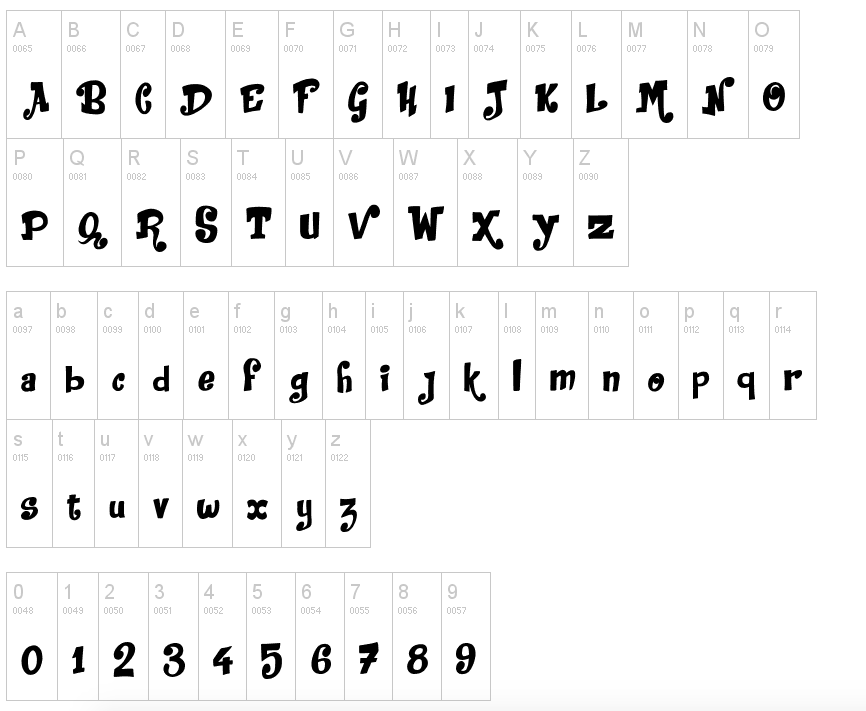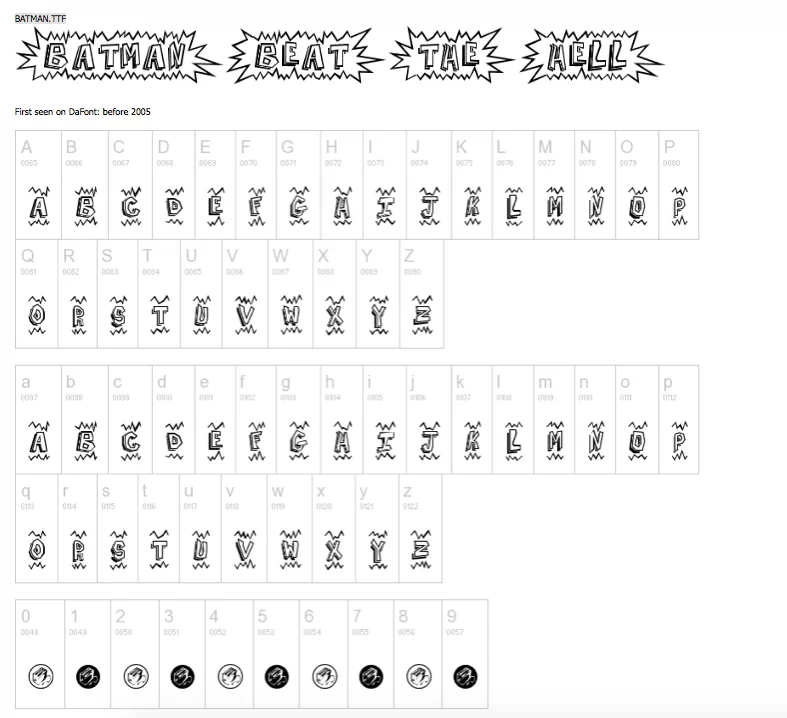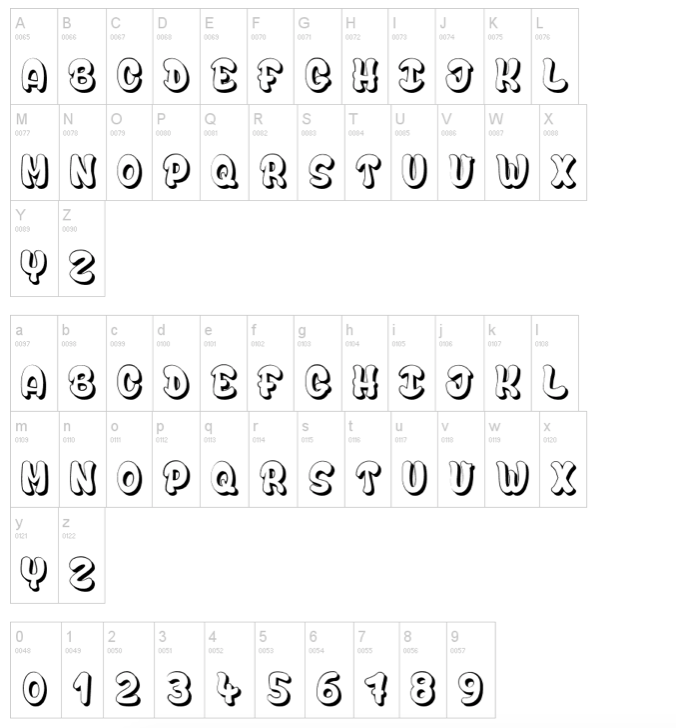
Die 20 besten Zeichentrick- und Comic-Schriftarten
Veröffentlicht: 2022-06-30Comics und Zeichentrickbücher dienen der Unterhaltung. Sie sollten in keiner Weise langweilig oder repetitiv sein. Nicht nur guter Inhalt, sondern auch erstaunliche Grafiken sind hilfreich, um Ihr Comicbuch zu einem Bestseller zu machen.
Abgesehen von Bildern spielt der Schriftstil Ihres Buches eine große Rolle bei der Gewinnung von Lesern. Die Verwendung des gleichen Schriftstils über Jahre hinweg ist für Ihre Leser ab einem bestimmten Punkt möglicherweise nicht mehr ansprechend.
Daher ist es ratsam, Ihren Schreibstil ständig mit ansprechenden Schriftarten zu aktualisieren, um sich besser zu engagieren.
Wir haben die konformistische Welt der Comic Sans Ms verlassen, um innovative Cartoon- und Comic-Schriftarten auszuwählen, die den Inhalt stilvoller, funkiger und unterhaltsamer aussehen lassen.
Werfen Sie einen Blick auf coole, ausgefallene Zeichentrick- und Comic-Schriftarten , die Ihren Inhalten zusätzlichen Schwung verleihen können.
FETT GEDRUCKT
Wenn Sie ein paar Wörter hervorheben oder die Aufmerksamkeit der Leser sofort auf sich ziehen möchten, ist Fettschrift perfekt. Schauen Sie sich die trendigen fetten Schriftarten an, die sofort ins Auge fallen.
Badaboom
Badaboom ist eine perfekte Schriftart für Ausrufe und Titel. Inspiriert von der Kunst jahrelanger Comics, ist es sicherlich eine beeindruckende Schriftart zum Ausprobieren.
Das Erstaunliche ist, dass Sie keinen einzigen Cent ausgeben müssen, um es zu benutzen. Es kommt sowohl im OPENTYPE- als auch im TRUETYPE-Format. Im Laufstil gestaltet, ist es informell und passt daher gut zu lustigen Comics.
Super Mario 2
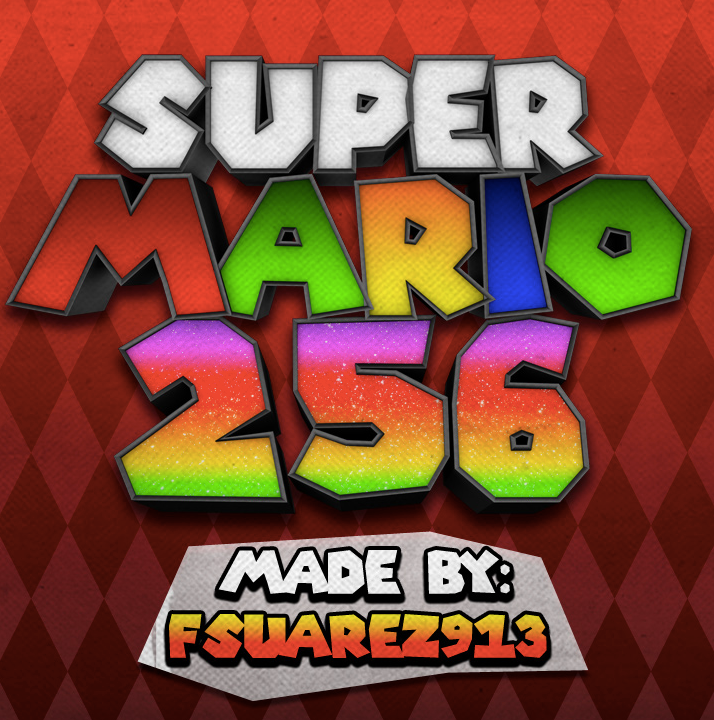
Es könnte nichts Besseres geben als Super Mario 2, um dramatische Titel oder Schlagzeilen zu machen. Es ist robust und dennoch stilvoll und peppt Ihre Inhalte perfekt auf.
Diese Schriftart ist vom Mario-Schriftzugstil inspiriert, der erstmals auf dem Titelbildschirm von Super Mario Bros.3 zu sehen war. Kühn und einflussreich, SuperMario 2 ist ein besonderer Leckerbissen für Ihr Comic- und Zeichentrickbuch.
Zurück Probleme
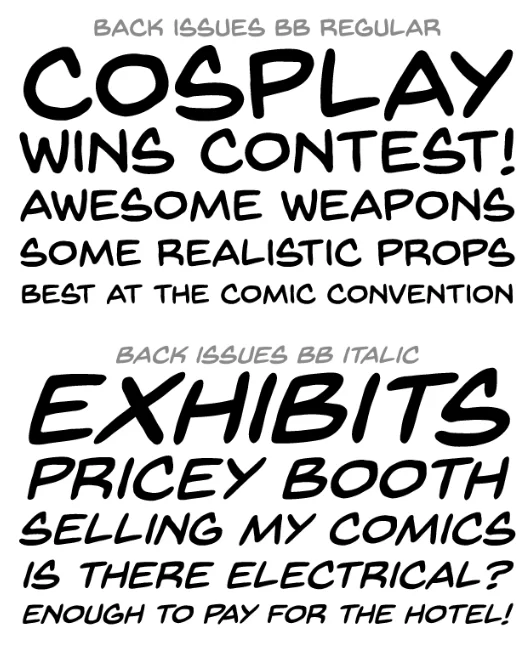
Back Issues kommt im Laufstil und sieht am besten mit humorvollen Inhalten aus. Es ist in normaler, fetter und kursiver Schrift verfügbar, um mit Ihren Inhalten so zu spielen, wie Sie möchten.
Für ästhetisch ansprechende Geschichten und Dialoge können Sie frühere Ausgaben in MAC TTF, OPENTYPE und PC TFF herunterladen. Es hat eine beruhigende Wirkung auf die Augen und fügt dem Inhalt ein interessantes Element hinzu.
SPASS
Karikatur
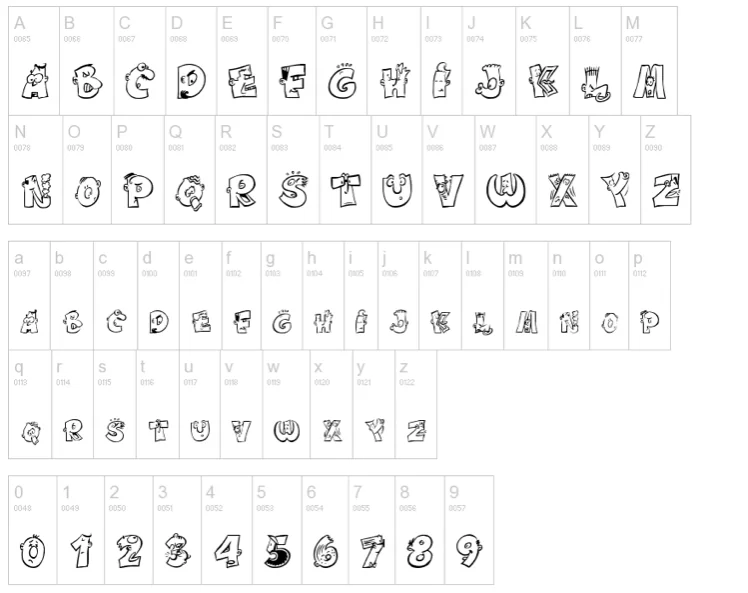
Karikatur ist ein ansprechender Schriftstil, der selbst ein gewöhnliches Gespräch lesenswert machen kann. Jeder einzelne Buchstabe dieses Schriftstils ist durchdacht gestaltet, um die Dinge fast sofort interessant zu machen.
Nicht nur alphabetische Buchstaben, sondern auch Zahlen und verschiedene Zeichen in Caricature, von denen jedes einem lustigen Gesichtsausdruck ähnelt, um Ihrem Buch einen Mehrwert zu verleihen.
Skizzenhafter Comic
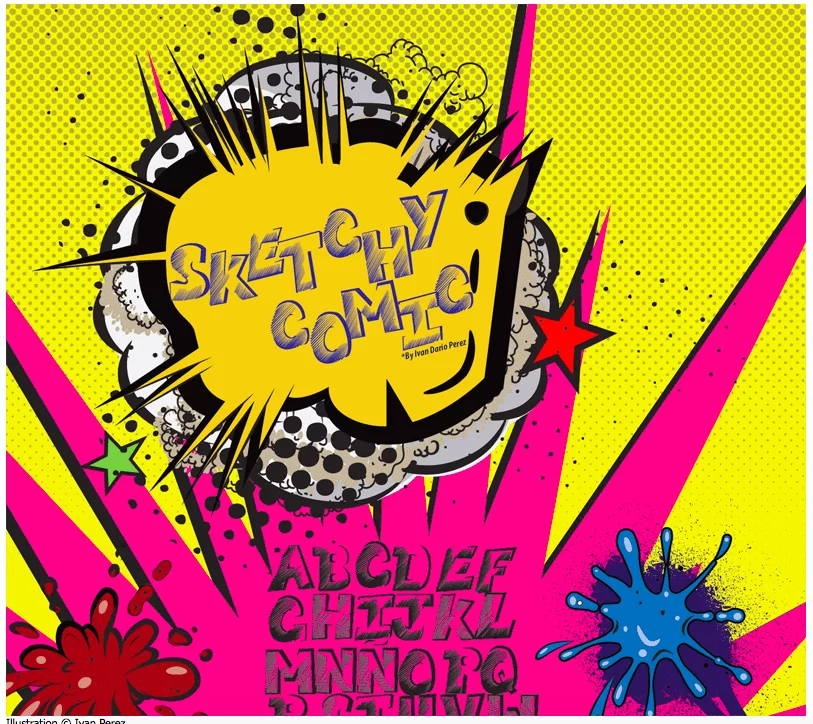
Liebhaber des Skizzierens werden Sketchy Comic nicht widerstehen können. Jeder Buchstabe und jedes Symbol dieser Schriftart hat einen Hauch von Skizze, um Ihrem Buch eine persönliche Note zu verleihen.
Es ist eine einfache, aber interessante Möglichkeit, ansonsten langweilige Inhalte ansprechend aussehen zu lassen.
Boyz R Gross NF-Schriftfamilie
Boyz R Gross NF Font Family ist eine weitere interessante Option, um Ihrem Comic ein lustiges Element zu verleihen. Dieser kurvige, zarte und schlanke Schriftstil hat eine zeitgemäße Anziehungskraft.
Wenn Sie also nach einem modernen Update suchen, probieren Sie diese Robotic Attack-Schriftart aus. Die einzigartige Ausstrahlung dieser Schrift macht sich gut in Comics mit minimalem Inhalt.
ELEGANT
Cheri
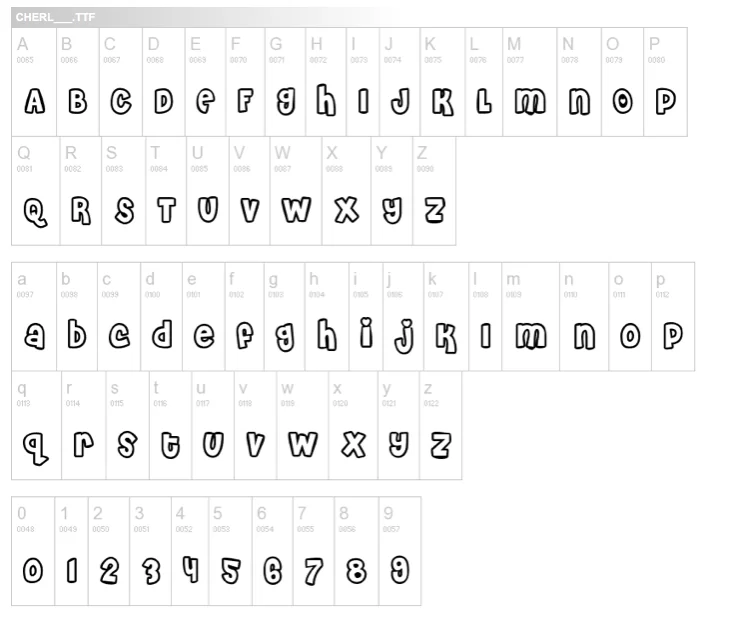
Cheri ist eine niedliche und angenehme Art, Ihre Comics zu schmücken. Alphabetische Buchstaben haben eine subtile Eleganz, während Zeichen und Symbole von Cheri mit einem kreativen Twist gestaltet sind.
Geben Sie Ihrem Comic-Schreibstil mit Cheri ein erfrischendes Update und machen Sie sich bereit, viele Komplimente einzusacken.
Jellygurp
Jellygurp ist ein ansprechender Schriftstil, mit dem Ihre Inhalte gleichzeitig stilvoll und elegant aussehen. Sie können mit verschiedenen Ebenen herumspielen, um Ihr personalisiertes handgefertigtes Design zu erhalten.
Es hat Ligaturen für Doppelbuchstaben und eine alternative Version für Kleinbuchstaben. Die weiche und charmante Jellygurp-Schrift hat das Potenzial, Leser zu umwerben.
Minni
Das Schriftbild von Minnie ist geradlinig und nüchtern. Diese Schriftart hat ein rätselhaftes Design, um mit den Lesern in Kontakt zu treten. Es ist Märchenbüchern für Kinder gewidmet, Zeichentrickfilmen wie Micky Maus.
Die sanfte Anziehungskraft dieser Schriftart eignet sich perfekt, um über Märchen, Disney-Figuren und Prinzessinnengeschichten zu schreiben.
Es gibt alphabetische Buchstaben in Großbuchstaben, Kleinbuchstaben, Zahlen und die am häufigsten verwendeten Zeichen und Symbole – ein komplettes Paket, mit dem Sie Ihren Comic fehlerlos fertigstellen können. Gehen Sie mit Shooting Stars so verträumt und phantasievoll vor, wie Sie möchten.
Wenn Sie jetzt so viele Möglichkeiten haben, kreative Elemente in Ihre Comics und Märchenbücher zu integrieren, denken Sie nicht viel darüber nach.
Beflügeln Sie Ihre Fantasie mit den coolen Schriftarten, die wir mit Ihnen geteilt haben.